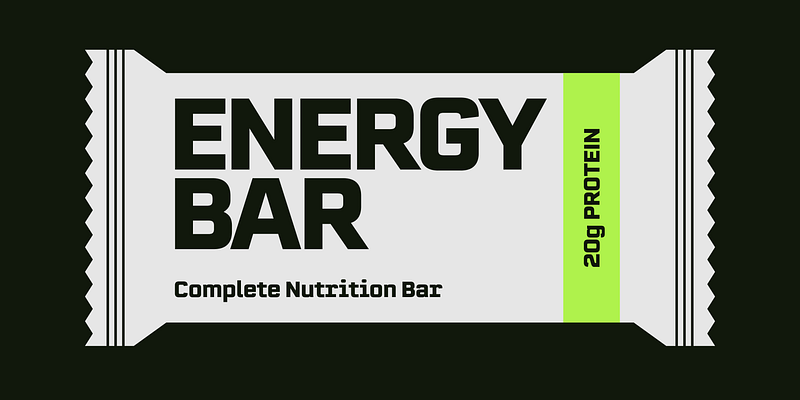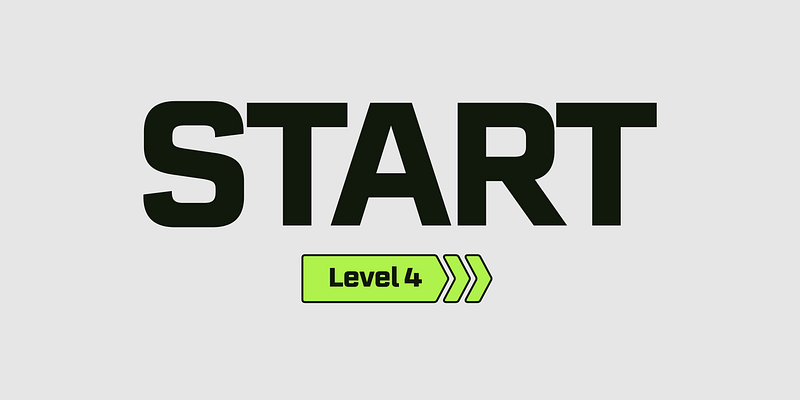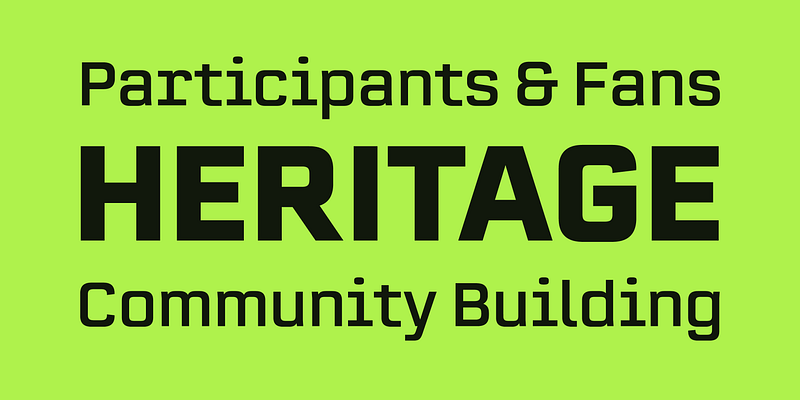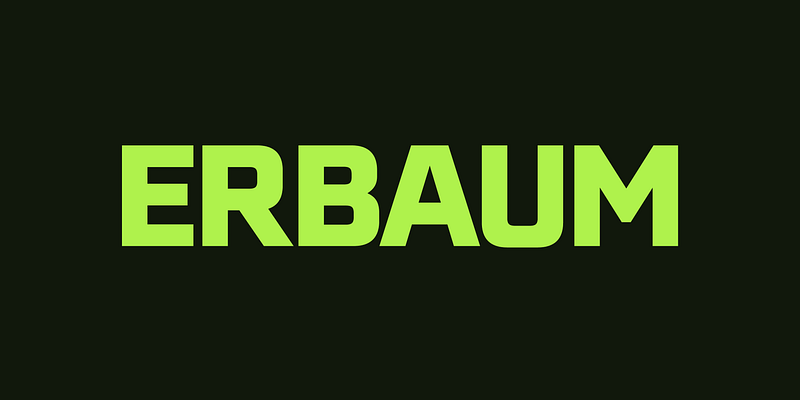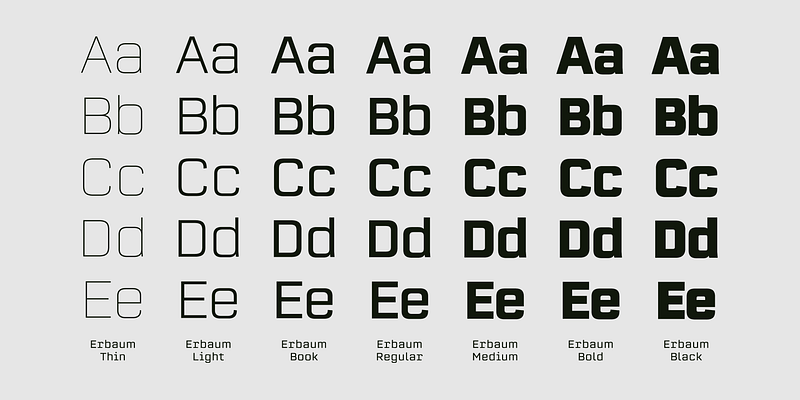
「Erbaum」は、正方形のディスプレイサンセリフ体ファミリーです。全体的な構造は単純明快で、細部はシンプルで合理的です。Erbaumは、構造と実用的な美学に重点を置いて、極力明確になるようにデザインされています。この書体の背後にあるコンセプトは、徹底的な機能重視の姿勢であり、コミュニケーションのための明確で効果的な手段と、前述のカテゴリの類似フォントに対するモダンな代替手段を提示することでした。拡張された x ハイトとシャープなディテールにより、読みやすさが向上します。その他の機能には、7 つのウェイト、キリル文字、代替文字、様々な OpenType 機能があります。